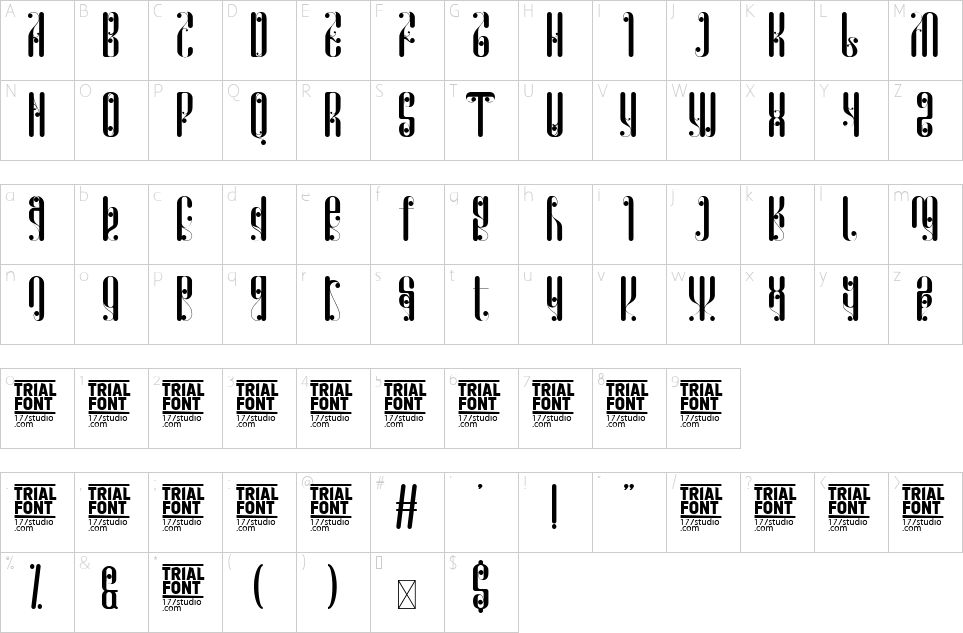
Descubra a riqueza visual da fonte Paintings Condensed, uma opção grátis e elegante para desafiar seu design gráfico. Desenvolvida pelo designer desconhecido de 177studio.com, esta fonte está disponível tanto para sistemas Windows quanto para Mac. As linhas finas e os detalhes sutis da Paintings Condensed adicionam um toque único e moderno a qualquer projeto gráfico que você realize. Seja você um profissional ou um entusiasta do design gráfico, a Paintings Condensed é uma excelente escolha para adicionar um toque diferenciado e único a suas criações. Com um design minimalista que destaca a essência do texto, esta fonte é uma ótima opção para quem busca uma fonte que se destaca sem ser vulgar. Descubra a beleza da Paintings Condensed e faça seu design se destacar ainda mais.